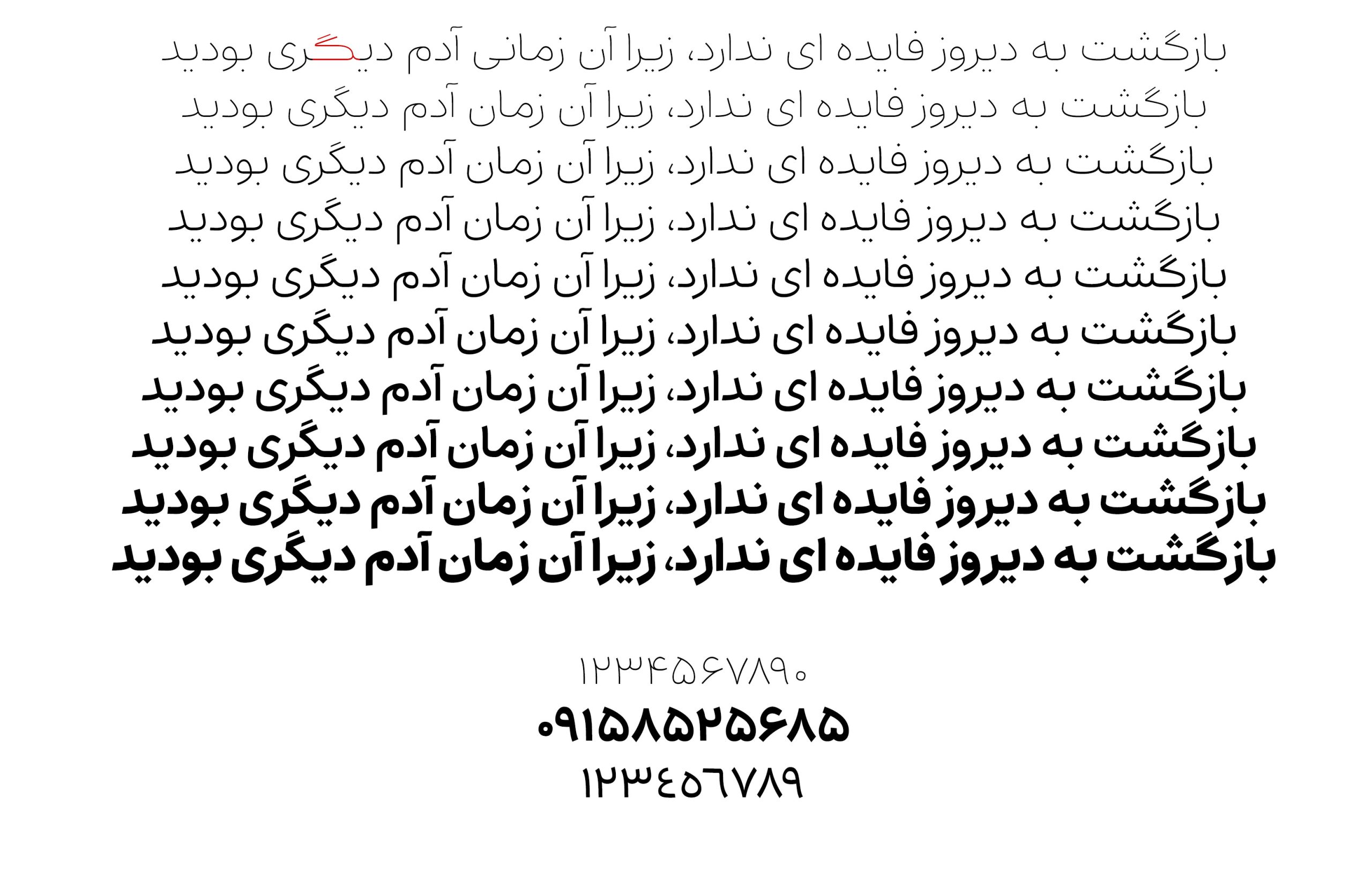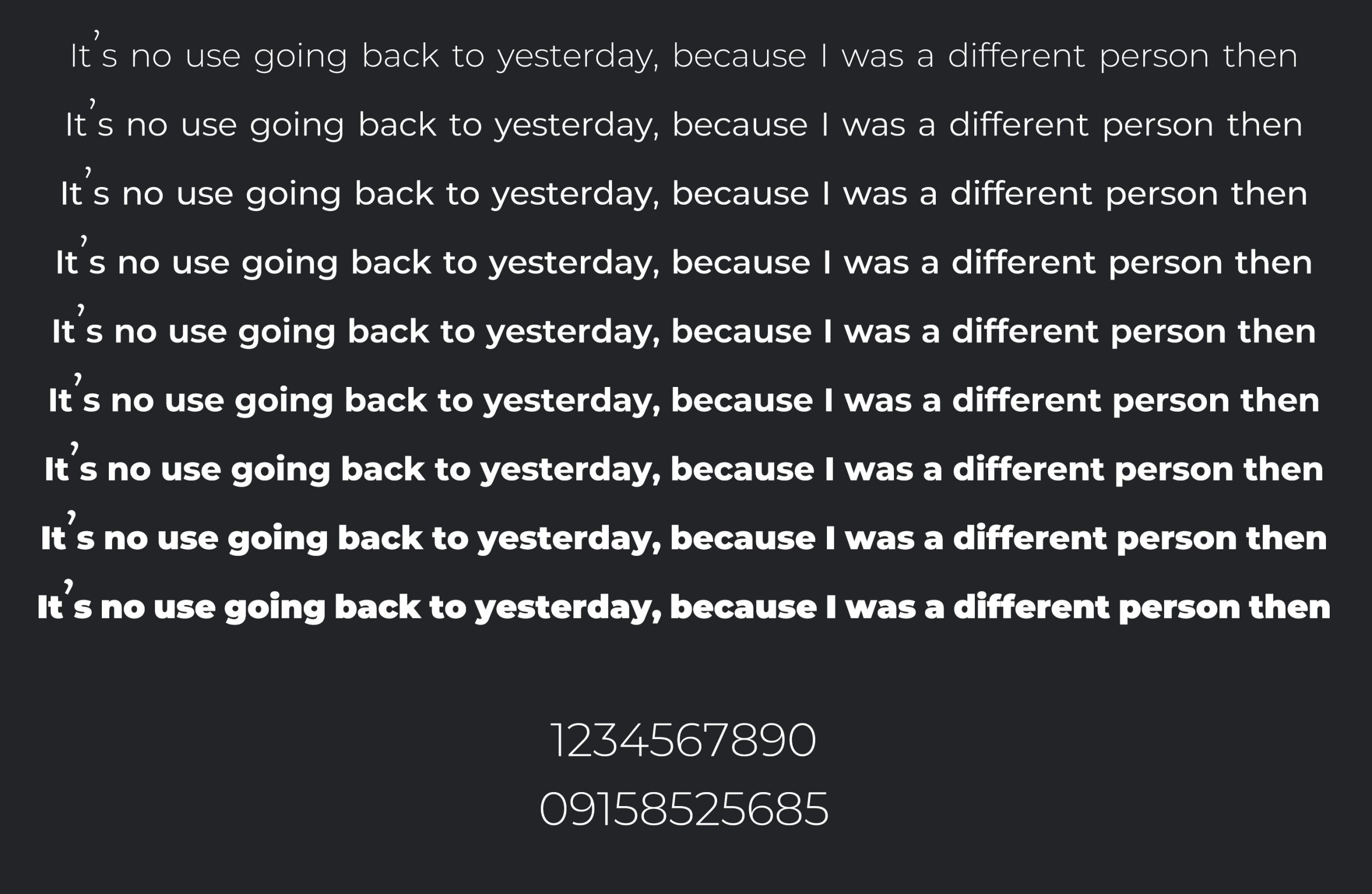
9 فونت نیما فارسی
دانلود مجموعه کامل فونت Nima فارسی Font اپیک نیما |
| ⭐ توضیحات | مجموعه ای کامل از فونت های نیما و نسخه شبیه سازی شده بنام اپیک نیما فونت اپیک نیما با پشتیبانی از حروف فارسی / انگلیسی ( لاتین) ، اعداد فارسی Fu Num بهمراه نسخه وب بهمراه فونت متغییر وریبل |
فونت نیما یک فونت انسان گرایانه مدرن برای نمایشگرهای دیجیتال
فونت نیما یک فونت انسان گرایانه مدرن است که برای استفاده در نمایشگرهای دیجیتال طراحی شده است. این فونت از حروف نگاری سنتی و خوشنویسی الهام گرفته و با رعایت اصول طراحی تایپفیس، خوانایی و زیبایی را به همراه دارد. در این مقاله، ما به بررسی ویژگیها، مزایا، کاربردها و نحوه خرید فونت نیما خواهیم پرداخت.
مقدمه
فونت نیما یک فونت جدید و منحصر به فرد و یک طراح تایپفیس ایرانی، در سال 2023 خلق شده است. این فونت با هدف ارائه یک فونت با کیفیت و مناسب برای زبان فارسی و سایر زبانهای دارای حروف عربی، به وجود آمده است. فونت نیما با تلفیق حروف نگاری سنتی و خوشنویسی با سبکهای مدرن و جذاب، یک فونت انسان گرایانه را ارائه میدهد که هم برای محصولات دیجیتال و هم برای محصولات چاپ شده مناسب است.
فونت نیما دارای بسیاری از ویژگیها و مزایای منحصر به فرد است که در ادامه به آنها خواهیم پرداخت. این فونت دارای حروف جایگزین و تغییرات خودکار است که باعث میشود حروف به صورت هوشمندانه با هم تطبیق پیدا کنند و شکل زیباتر و مناسبتر را به نمایش بگذارند. همچنین، این فونت دارای قابلیت وريبل فونت است که به شما اجازه ميدهد تغييرات ريز در ضخامت، عرض، شيب و قطعيّت حروف را اعمال كنيد. علاوه بر این، این فونت دارای اعداد همعرض است که برای نمایش دادههای عددی در جدولها، نمودارها و گزارشها بسیار مناسب است.
دانلودفونت نيما را ميتوانيد در بسياري از كاربردهاي طراحي استفاده كنيد. اين فونت براي طراحي وب و اپليكيشن، طراحي گرافيك و چاپ، طراحي لوگو و برندينگ، طراحي تابلو و بروشور، طراحي كتاب و مجله، طراحي پست و استوري، طراحي دعوتنامه و كارت تبريك، طراحي تصاوير پسزمينه و آبجكت، طراحي تصاوير مفهومساز و اينفوگراف و طراحي تصاوير شعار و جملات نقل قول مناسب است. در ادامه مقاله، ما به نمونههایی از هر یک از این کاربردها خواهیم نگاه کرد.
چرا فونت نیما؟
فونت نیما یک فونت منحصر به فرد و متمایز است که دارای بسیاری از ویژگیها و مزایای جذاب است. در این بخش، ما به برخی از این ویژگیها و مزایا خواهیم پرداخت و دلایلی را برای انتخاب فونت نیما بیان خواهیم کرد.
انسان گرایانه و مدرن
فونت نیما یک فونت انسان گرایانه است که با توجه به روح و روان خواننده طراحی شده است. این فونت با الهام از حروف نگاری سنتی و خوشنویسی، حروف را به شکلهای زیبا و جذاب تبدیل کرده است. این فونت با حفظ هویت زبان فارسی، سبکهای مدرن و جدید را به کار گرفته است. این فونت با استفاده از خطهای منحنی، نقطهچین، تغییرات ضخامت و شکستگیهای ظریف، حروف را زنده و پرحرکت کرده است. این فونت با تعادل بین سادگی و تنوع، خلاقیت و هماهنگی، دلپذیری و قابل اعتمادی را به خواننده منتقل میکند.
خوانایی و زیبایی
فونت نيما يك فونت با خوانايي بالا است كه براي استفاده در نمايشگرهاي ديجيتال طراحي شده است. اين فونت با رعايت اصول طراحي تايپفيس، مثل كنتراست، پروپورشن، كرنينگ، ليدينگ و تركيبپذيري، خواندن متون را براي خواننده آسان كرده است. اين فونت با دقت بالا در جزئيات حروف، مثل شكل، ابعاد، فضاسازي و تطبيق، حروف را به صورت شفاف و روشن به نمايش ميگذارد. اين فونت با تولید تبایید بین حروف، کلمات، جملات و پاراگرافها، سلسله مراتب معنایی را در متون ایجاد میکند. این فونت با همخوانی بین شکل حروف و معانی آنها، زبان را به صورت هولستیک (کلبین) به خواننده منعکس میکند.
دانلودپشتیبانی از زبانهای مختلف
فونت نيما يك فونت چندزبانه است كه پشتيباني كامل از زبان فارسي و ساير زبانهاي داراي حروف عربي را دارد. اين فونت شامل ۱۰۰۰ حرف، علامت و سمبل است كه براي نمايش متون در زبانهاي مختلف، مثل عربي، اردو، پشتو، كردي، آذري، تركي، ارمني، اوزبكي و … مناسب است. اين فونت با رعايت قواعد خاص هر زبان، مثل جهتگيري، اتصال، تشكيل و اعراب، حروف را به صورت صحيح و مطابق با استانداردها به نمايش ميگذارد. اين فونت با توجه به ويژگيها و نيازهاي هر زبان، مثل شكل حروف، فضاسازي، تناسب و تعادل، حروف را به صورت هماهنگ و همسو با هم نشان ميدهد.
حروف جایگزین و تغییرات خودکار
فونت نیما یک فونت هوشمند است که دارای حروف جایگزین و تغییرات خودکار است. این فونت با تشخیص موقعیت حروف در کلمه، مثل ابتدا، وسط، انتها و جدا، حروف را به شکلهای مختلف نشان میدهد. این فونت با تشخیص نوع حروف قبل و بعد، مثل حروف بالا، پایین، چپ و راست، حروف را به صورت مناسب با هم اتصال میدهد. این فونت با تشخیص کلمات خاص، مثل الله، محمد، بسم و …، حروف را به شکلهای زیبا و خوشنویسانه نمایش میدهد. این فونت با تشخیص علامات نگارشی، مثل نقطه، ویرگول، علامت سوال و …، حروف را به صورت منطبق با علامات تنظیم میکند.
وريبل فونت و اعداد همعرض
فونت نيما يك فونت وريبل است كه به شما اجازه ميدهد تغييرات ريز در ضخامت، عرض، شيب و قطعيّت حروف را اعمال كنيد. اين فونت با استفاده از تكنولوژي جديد وريبل فونت، به شما امكان ميدهد كه براساس نياز و سليقه خود، فونت را تغيير دهيد. شما ميتوانيد با كشيدن نوار لغزان در نرمافزار طراحي خود، ضخامت حروف را از باريك ترين تا كلفت ترين شكل ممكن تغيير دهيد. همچنين شما ميتوانيد عرض حروف را از كوچك ترين تا بزرگ ترين اندازه ممكن تغيير دهيد. شما همچنین میتوانید شیب حروف را از صاف ترین تا کج ترین حالت ممکن تغییر دهید. شما همچنین میتوانید قطعیّت حروف را از نرم ترین تا سخت ترین شکل ممکن تغییر دهید.
برای مثال، شما میتوانید فونت نیما را برای طراحی یک تصویر مفهومساز و اینفوگراف برای یک پروژه علمی، پژوهشی، آموزشی، تجاری، سیاسی، اجتماعی، فرهنگی، هنری، سلامتی، ورزشی، خبری، تفریحی و … استفاده کنید. شما میتوانید با استفاده از سطح شخصي فونت نيما، يك تصوير مفهومساز و اينفوگراف را براي خود يا كسي كه ميشناسيد طراحي كنيد. شما ميتوانيد با استفاده از سطح تجاري فونت نيما، يك تصوير مفهومساز و اينفوگراف را براي يك كسب و كار كوچك يا متوسط طراحي كنيد. شما ميتوانيد با استفاده از سطح سازماني فونت نيما، يك تصوير مفهومساز و اينفوگراف را براي يك سازمان بزرگ يا چندين كسب و كار طراحي كنيد. شما ميتوانيد با استفاده از سطح دولتي فونت نيما، يك تصوير مفهومساز و اينفوگراف را براي يك دولت يا چندين سازمان دولتي طراحي كنيد.